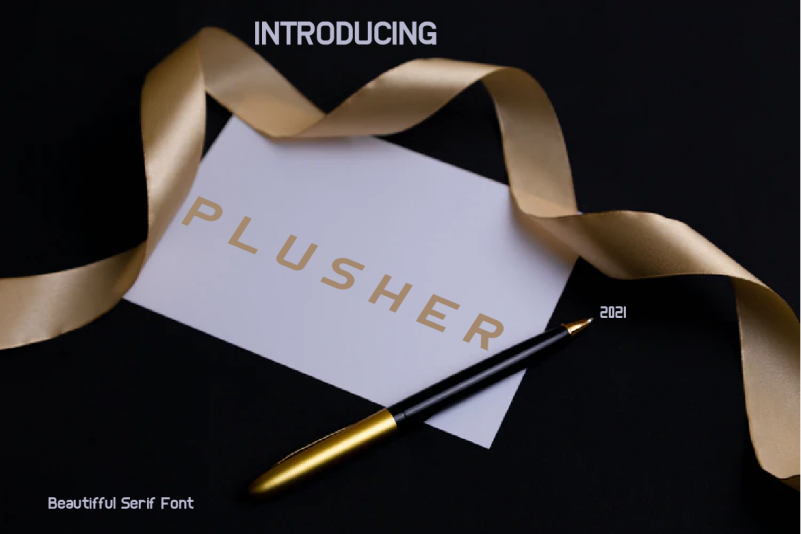
Esta fonte foi criada especificamente para fins de exibição de texto, trazendo uma sensação moderna e poderosa às suas criações. Com seu estilo elegante e sofisticado, é ideal para usar como texto principal ou cabeçalho no design de plantéis ou layout web. A fonte ‘Pleshur’ oferece um nível adicional através da inclusão de um glyph alternativo, tornando-a ainda mais versátil em termos de ajustes e personalização. Para quem está sempre à procura do próximo hit visual, a fonte Plusher é uma ótima escolha.